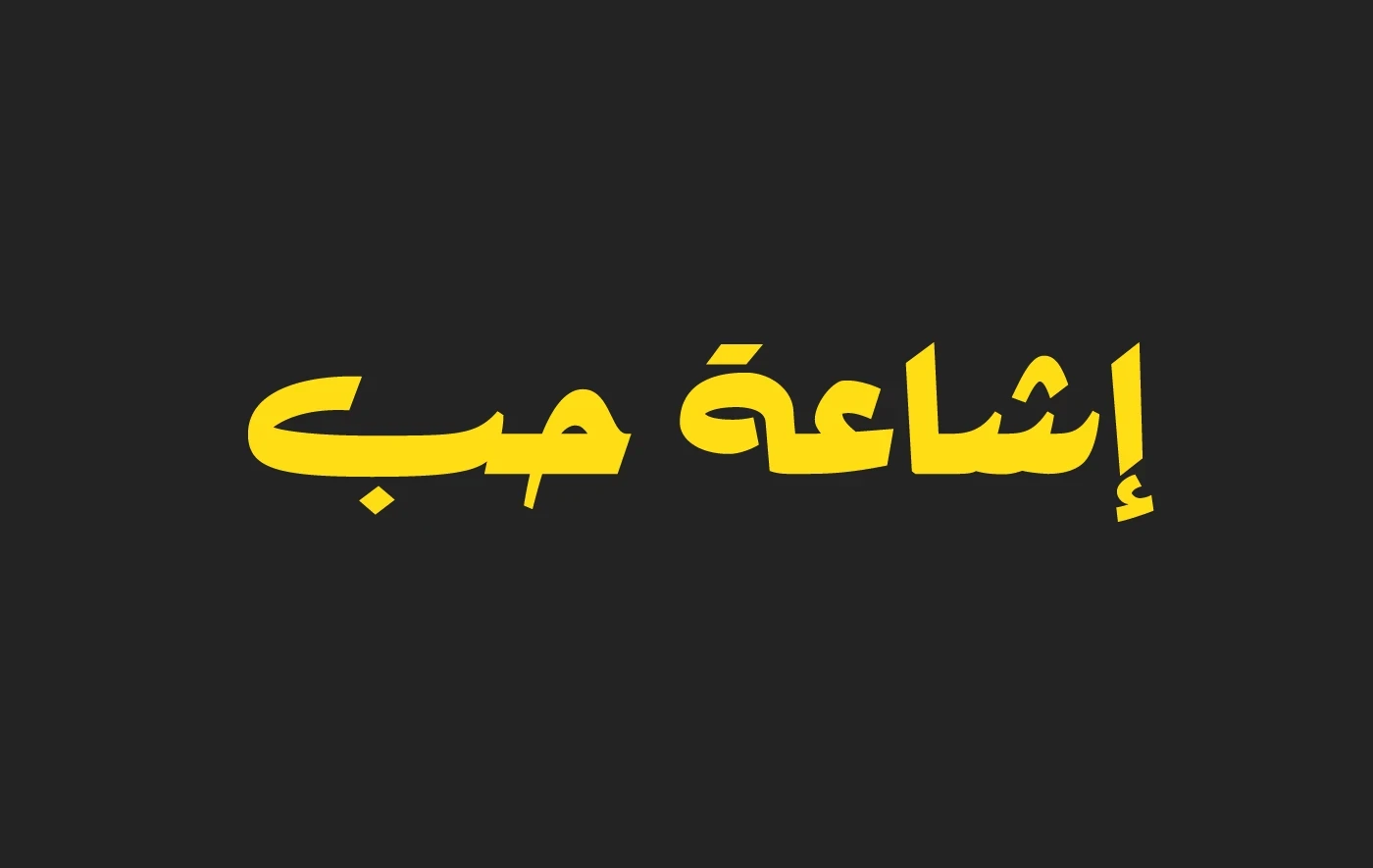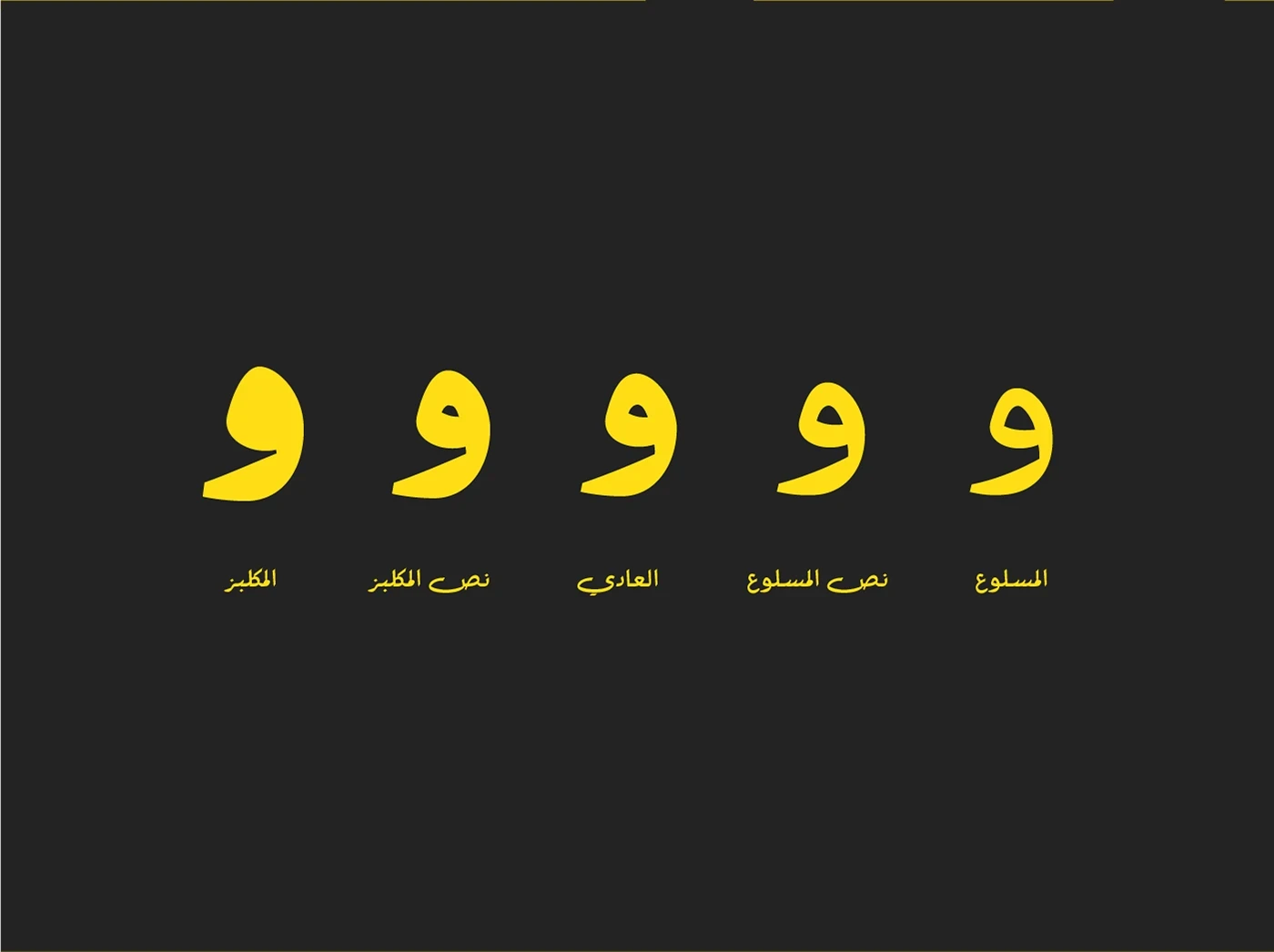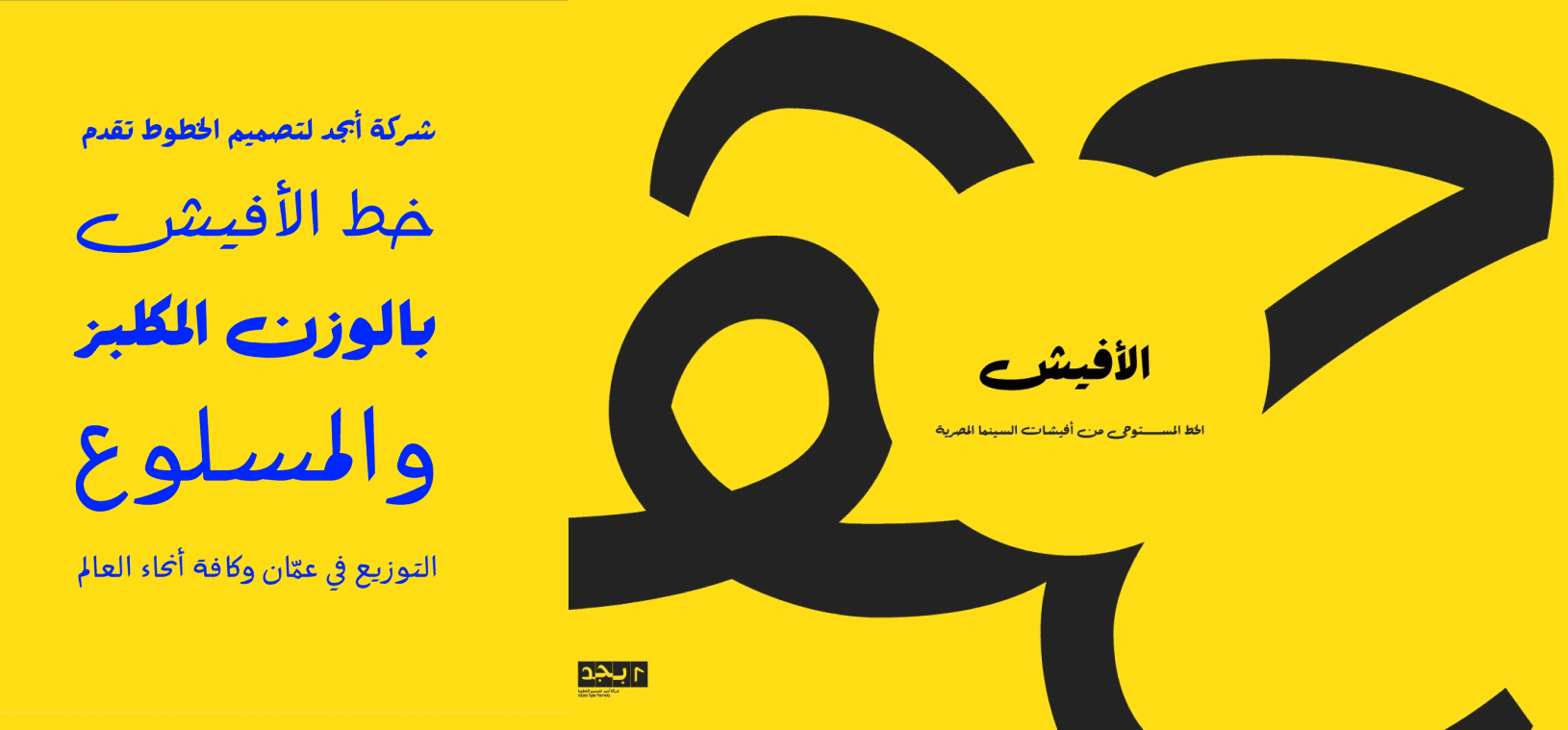
خط "أفيش" هو محاولة لإنشاء عائلة خطوط قوية ومتينة، مستندة إلى أسلوب الخط الرقعة. يعتمد في تصميمه على الأسلوب المصري في كتابة الرقعة، والذي كان شائعًا جدًا في ملصقات الأفلام خلال فترة الخمسينيات حتى السبعينيات.
يأتي الخط بمجموعة واسعة من التراكيب (Ligatures) وميزات OpenType مثل الزخارف (Swash) والبدائل الأسلوبية.
يدعم الخط اللغات: العربية، الفارسية، الأردية، بالإضافة إلى الكردية.
خط "أفيش" هو محاولة لإنشاء عائلة خطوط قوية ومتينة، مستندة إلى أسلوب الخط الرقعة. يعتمد في تصميمه على الأسلوب المصري في كتابة الرقعة، والذي كان شائعًا جدًا في ملصقات الأفلام خلال فترة الخمسينيات حتى السبعينيات.
يأتي الخط بمجموعة واسعة من التراكيب (Ligatures) وميزات OpenType مثل الزخارف (Swash) والبدائل الأسلوبية.
يدعم الخط اللغات: العربية، الفارسية، الأردية، بالإضافة إلى الكردية.
خط "أفيش" هو محاولة لإنشاء عائلة خطوط قوية ومتينة، مستندة إلى أسلوب الخط الرقعة. يعتمد في تصميمه على الأسلوب المصري في كتابة الرقعة، والذي كان شائعًا جدًا في ملصقات الأفلام خلال فترة الخمسينيات حتى السبعينيات.
يأتي الخط بمجموعة واسعة من التراكيب (Ligatures) وميزات OpenType مثل الزخارف (Swash) والبدائل الأسلوبية.
يدعم الخط اللغات: العربية، الفارسية، الأردية، بالإضافة إلى الكردية.